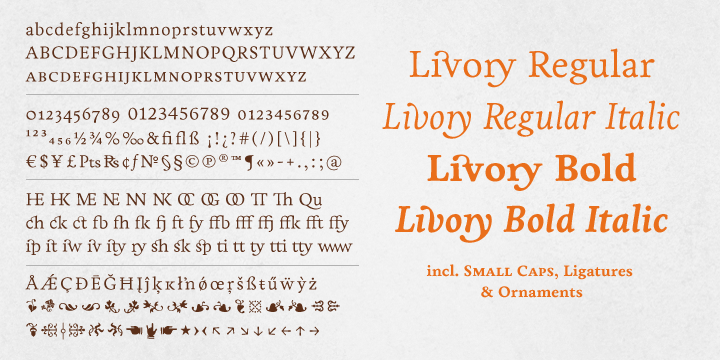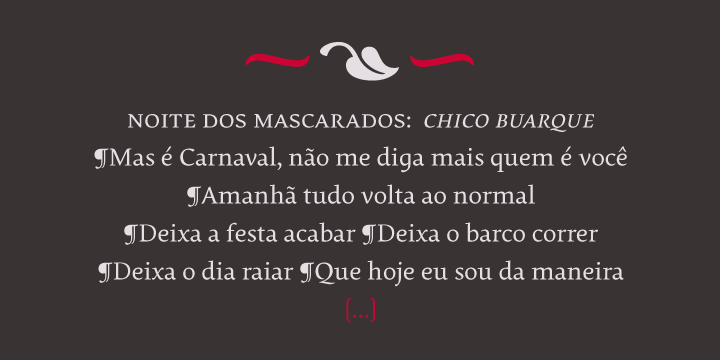
Suche schöne Serifenschrift
ich bin gerade dabei, ganz klassische Visitenkarten für eine Bekannte (privat, keine Fa.) zu erstellen.
Vom Layout wie von der Gestaltung total einfach bleiben: Keine Bilder, keine Farben, keinen auffälligen Schriftsatz, usw.
Das einzig feine Element soll die Schriftart sein; und das Papier.
Ich möchte unbedingt eine Serifenschrift, finde aber keine passende.
Es sollte nicht zu sehr an die Times erinnern, sollte sehr elegant (aber gleichzeitig nicht prätentiös) sein, und nicht zu eckig - man sollte (trotz der klassisch-nüchternen Karte) gleich vom Schriftbild erkennen, dass es die Visitenkarte einer FRAU ist; deswegen soltte es aber noch lange keine echte Kitsch-Schrift oder was Schreibschriftartiges sein.
Vielleicht fällt von Euch SpezialistInnen jemandem was ein (gerne auch Freeware :-))
Bei den kommerziellen Kandidaten denke ich an die Corda (von Hoftype) und die Livory (von HvD Fonts). Beide auch als Webfont zu haben.
Bei der Livory sind es vor allen die Ligaturen, die den weiblichen Akzent setzen könnten. Da ist die Frage, ob der Visitenkarten-Text Anwendungen dafür hergibt.
Ich kann dafür immer nur wieder meinen All-Time-Favourit vorschlagen:
(aber unbedingt die Original und nicht die Next, die Unterschiede sind in der Italic sehr deutlich)
Von Hoftype wären vielleicht auch noch die Argos und die neue Ashbury interessant. Letztere bietet sogar einen kostenlosen Light-Schnitt.
Etwas eigenwillig aber dafür schön charakteristisch wäre die Pollen von Typetogether.
Es gibt hier im Forum immer wieder Anfragen die ich schon bezüglich ihrer Formulierung schlicht frech finde; die bedürfen dann auch einer »Abmahnung«. Ansonsten würde ich trotzdem zur »Gemütlichkeit« raten. Oder man formuliert es einfach als Frage: »Welche Schriften hast Du Dir denn schon angesehen die Dir gefallen?« Das verschreckt dann auch Neulinge nicht sondern »erzieht« (hoffentlich).
Ich habe mich vorhin gefragt, ob ich nicht zu viele Vorschläge gebracht habe. Da bewundere ich Schnitzel und Kathrin wie gezielt ihre Antworten ausfallen. Vielleicht hätte eine deutlichere Eingrenzung da für mich Abhilfe* geschaffen.
Daher finde ich auch gutenbergers Einwand nachvollziehbar. Aber vielleicht an andere Stelle noch dringlicher als hier, hat Margit doch schon mehr gesagt, als manch anderer. Also auch Dir Danke gutenberger für’s Nachhaken. Nach CRudolphs vorgeschlagener Verfahrensweise, trägt es in Zukunft bestimmt gute Früchte! :-D
* obwohl ich nicht wirklich daran glaube, bin wohl eher der Typ für’s Spektrum ; )
Wie wärs’s mit jener Richtung?
oder
Wenn man die jetzt noch irgendwo mit Mediävalziffern bekommen könnte …
War das Voraussetzung oder nur nice to have?
Bei übrigen Euros käme auch die Fedra in Frage …
War das Voraussetzung oder nur nice to have?